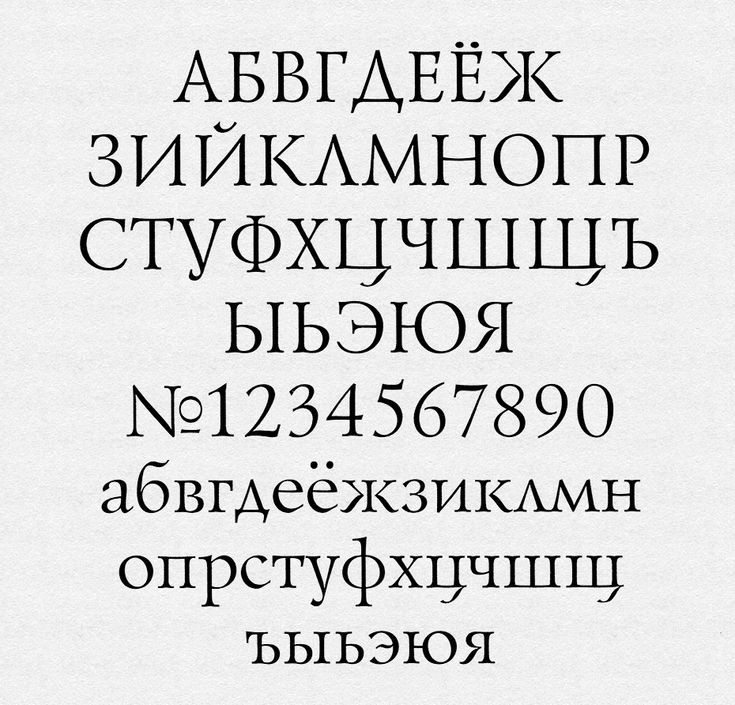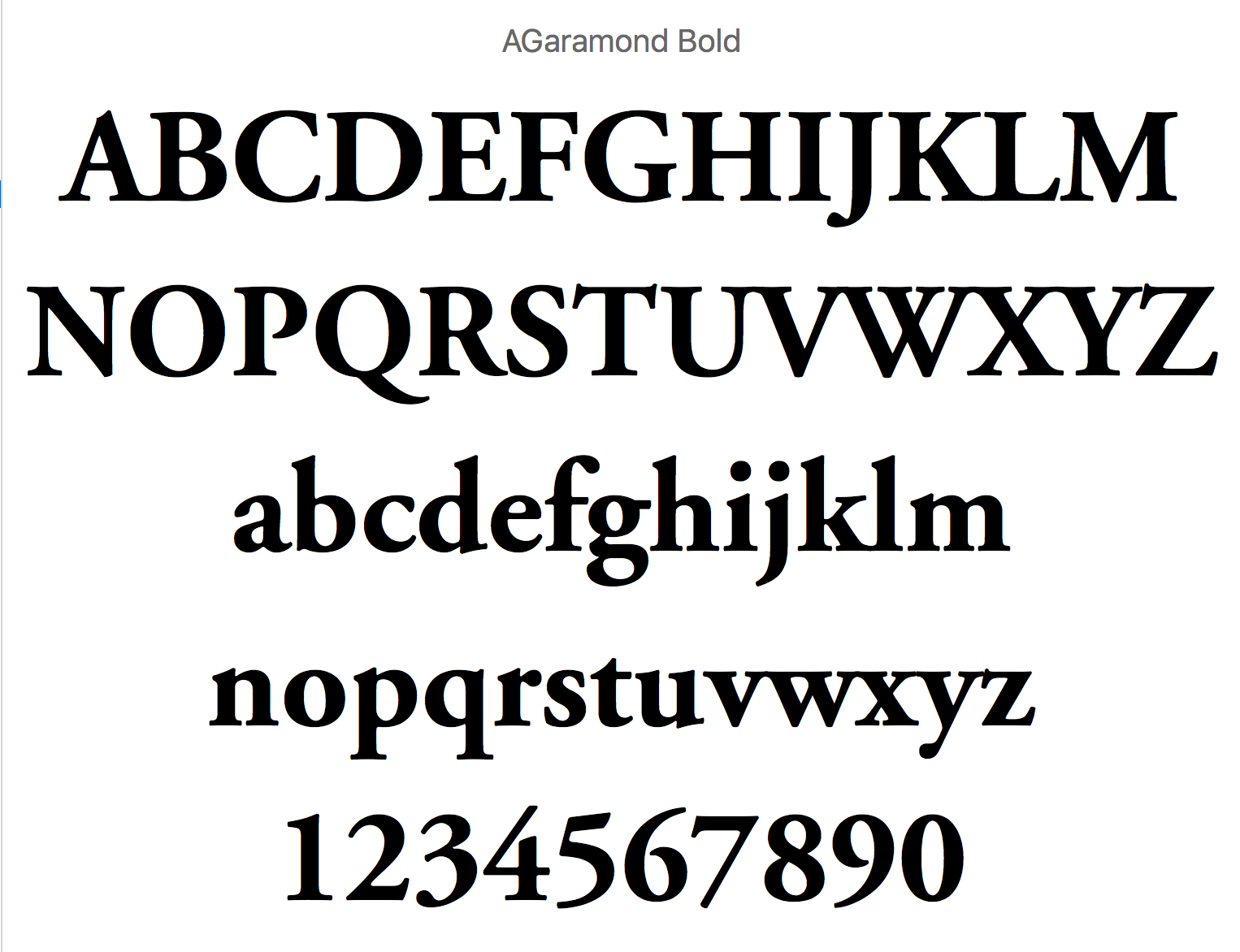
Наиболее часто используемые гарнитуры с засечками
Работа со шрифтами подразумевает понимание того, какие шрифты используются чаще всего в каждом из типов. Вы знаете, какие шрифты с засечками используются чаще всего? Волны Без засечек? Это то, что вы должны знать, чтобы знать тенденцию дизайна в то время или порвать с обычным и предложить клиенту что-то сверх обычного.
Итак, сегодня мы хотим сосредоточиться на наиболее часто используемые шрифты с засечками, Вы хотите знать, что это такое и почему? Мы вам тогда расскажем.
Что такое шрифт с засечками
Этот шрифт, также известный как serif, terminal или serifs, имеет орнаменты на концах персонажей, То есть на каждой букве есть красивый орнамент, который помогает сделать их визуально красивее.
Шрифт Serif отличается прежде всего тем, что он может меняться в зависимости от наклона, ширины, большого веса … Вот почему он делает его одним из лучших вариантов в зависимости от того, какие проекты. Например, для книг, логотипов, плакатов и т. Д. В общем, любой длинный текст может выиграть от этого шрифта, потому что он облегчает чтение, а также создает своего рода воображаемую строку, чтобы не потеряться.
Что передает шрифт Serif?
Шрифт с засечками считается одним из самых классических. Потому что, Иногда это называют «римской типографикой», потому что она передает эту формальность, сохранение, традицию и т.
Конечно, сегодня существует два типа засечки, древнеримские, чьи засечки уточняются по мере того, как они достигают крайности; и современные римские, сохраняющие толщину всей буквы.
Однако все они дают ощущение серьезности, авторитета, культа … Следовательно, они широко используются, особенно в книгах и образовательных проектах, благодаря своей трезвости.
Наиболее часто используемые шрифты с засечками
Как мы уже говорили, шрифты с засечками являются частью нашей повседневной жизни. Газеты, журналы, книги, учебники и др. Они предлагают нам этот тип шрифта, и мы рассматриваем их как нечто естественное, хотя мы не знаем, что они так называются.
Но из всех типов этого типа, какие шрифты с засечками используются чаще всего? Если хотите знать, мы поговорим о них ниже.
Times New Roman, один из наиболее часто используемых шрифтов с засечками
Это один из самых известных, особенно потому, что Word использует его с самого начала, и мы знаем это по работе с документами.
Он довольно четкий и имеет правильный размер, чтобы читать без особой головной боли.
Garamond
Garamond — один из самых используемых и распространенных шрифтов с засечками в мире. Если ты не знаешь Он был создан в XNUMX веке во Франции. Его создатель? Дизайнер Клод Гарамонд, отсюда и его имя.
Apple — одна из компаний, которые использовали его в течение многих лет, и он идеально подходит для учебников, веб-сайтов и т. Д.
Палатино Линотип
Это классический и распространенный шрифт с засечками, особенно в газетах, но также и в книгах, журналах и даже на веб-страницах, потому что они делают текст очень разборчивым.
Это системный шрифт, то есть установлен по умолчанию практически на всех компьютерах.
Книжник Старый Стиль
Это было разработан Онг Чонг Ва в 2005 году и имеет возможность предлагать вам до 12 шрифтов. Однако автор использовал более ранний шрифт Oldstyle Antique, разработанный в 1858 году компанией AC Phemister по заказу литейного завода Miller and Ricard в Эдинбурге, Шотландия.
После успеха многие другие американские компании создали различные версии книги, в результате чего появился Bookman.
Еще один из наиболее часто используемых шрифтов с засечками — Georgia.
Шрифт Georgia похож на шрифт Garamond, но более тонкий и плоский, чем Times New Roman. Он также меньше, поэтому занимает меньше места, чем другие буквы как и предыдущий, Bookman Old Style.
Как и те, о которых мы говорили, он хорошо известен, и мы установили его на компьютер.
Форум
Основанный на самых классических шрифтах, это один из наиболее широко используемых шрифтов с засечками, особенно в заголовках и заголовках. Однако это не значит, что его можно использовать только для этого.
Его создатель Денис Машаров придумал для использования в абзацах или длинных текстах.так как он выглядит довольно большим, и за ним легко следить.
Афина
Это один из наиболее широко используемых шрифтов с засечками, разработанный Мэттом Эллисом.
Можно сказать, что это один из самых классических (древнеримских). Почему? Ну, потому что окончания букв имеют тенденцию «утончаться» на концах, что характерно для этого типа шрифтов.
Однако в данном случае это придает ему смелый и в то же время эффектный вид, потому что, поскольку вся буква не одинакова, она привлекает внимание. В длинном тексте у вас не будет проблем с этим.
Бодони
Это один из наиболее часто используемых шрифтов с засечками, хотя его создание довольно старое. И сделал его создатель в 1787 году. Джамбаттиста Бодони была ветераном и опередила свое время. потому что он сделал шрифт современного кроя, который использовался во многих редакционных статьях, модных журналах и т. д.
Конечно, текущая версия — не та, которую делали в свое время. Этот новый называется Bauer Bodoni.
Плантен
Хотя это не очень известный шрифт, правда в том, что он был одним из самых используемых в 2020 году в гарнитурах с засечками, а это означает, что в этом году вы также можете рассмотреть его.
Используется в основном для редакционной работы, а также для непрерывных текстов. потому что его чтение очень приятно глазу и заставляет погрузиться прямо в текст, забыв обо всем остальном.
Часовой
Это один из наиболее часто используемых шрифтов с засечками с момента его создания в 2009 году. Его форма заставляет нас думать о курсиве, хотя буква не имеет прямого отношения к нему. Его легко понять, и в нем есть несколько строк, которые побуждают вас смотреть только на этот тип шрифта..
Есть еще много шрифтов с засечками, некоторые из характеристик этого шрифта даже выходят за рамки «нормального». Такие названия, как Book Antiqua, Libre Baskerville или Alegreya, — это лишь некоторые из других примеров наиболее часто используемых шрифтов с засечками, которые мы можем дать вам. Вы порекомендуете некоторые из них?
Шрифт с засечками
Объединенный институт ядерных исследований
- Информация о материале
- Категория: XX век.
Повседневная жизнь научного сотрудника
Не можем не поделиться с вами вот такой красотой: поздравительные адреса ручной работы. Это сейчас всё просто: скачал в яндексе фон для открытки и подходящее случаю стихотворение, выбрал шрифт, заполнил поздравление и распечатал на принтере.
А вот в XX веке… Главный секрет успеха — сотрудник с талантом каллиграфически писать. И другой, который умеет складно придумывать тексты. Невероятное терпение. Тушь и перо. Бритвенное лезвие для зачистки ошибок.
А если еще кто-то может акварелью выписать затейливую буквицу и нарисовать обложку…
На фото: поздравительные адреса к юбилеям Бруно Понтекорво от сотрудников ОИЯИ и других организаций.
Читайте также
Приглашаем на выставку «Рабочие будни научного сотрудника XX века»
08 апреля 2021
С 12 апреля по 12 августа приглашаем посетить выставку «Рабочие будни научного сотрудника XX века», приуроченную к 65-летию ОИЯИ!
В Музее истории науки и техники ОИЯИ представлены экспонаты из.
Пятничная рубрика: прощаемся и до скорой встречи в Музее ОИЯИ!
19 марта 2021
Дорогие друзья! Сегодня заключительный пост нашей пятничной рубрики «Повседневная жизнь научного сотрудника XX века», посвященной 65-летию нашего Института.
Стенгазета «Луч»
12 марта 2021
В прошлом выпуске мы писали о стенгазетах лабораторий ОИЯИ.
Праздничная стенгазета
05 марта 2021
Скоро праздник. Как тут не вспомнить о народном творчестве, которое кипело в кабинетах лаборатории в преддверии праздников и юбилеев, когда сотрудники создавали настоящие поздравительные шедевры для…
Говорят все радиостанции Советского Союза
26 февраля 2021
Сегодня человек с наушниками нам совершенно привычен.
Печатное слово
19 февраля 2021
Профессия машинистки, «женщины, работающей на пишущей машинке» (словарь Ушакова), уже ушла в прошлое. И хотя машинистка печатает быстро (и в этом смысле могла бы быть востребована и сегодня), ее уже…
Бумажная версия
12 февраля 2021
Споры между читателями электронных книг и приверженцами старой доброй бумаги давно утихли.
Войны остро- и тупоконечников не случилось. Кто-то полностью перешел на цифровые книги, кто-то остался…
Гарнитура из прошлого
05 февраля 2021
Вот такая трогательная гарнитура из прошлого века имеется в экспозиции Мемориального кабинета Бруно Понтекорво в ЛЯП ОИЯИ. Полагаем, что это устройство для делегатов международных конференций, с…
Шрифт с засечками
29 января 2021
Не можем не поделиться с вами вот такой красотой: поздравительные адреса ручной работы.
Это сейчас всё просто: скачал в яндексе фон для открытки и подходящее случаю стихотворение, выбрал шрифт,…
Миром правят числа
И снова мы делаем нашу рубрику совместно с Музеем истории науки и техники ОИЯИ. Потому что хотим рассказать о том, как считали в науке XX века. Точнее, производили большие и сложные расчеты,…
«Компактный, красивый, таинственно поблёскивающий…»
15 января 2021
Этот пост мы подготовили совместно с Музеем истории науки и техники ОИЯИ.
⠀
Цитата в заголовке о компьютере! Думаете, о новом смартфоне известной фирмы? Нет, это о вымышленном компьютере «Алдан-3″…
«Новый год, он не ждет, он у самого порога!»
25 декабря 2020
Дорогие друзья! В следующую пятницу мы с вами окажемся в новом, 2021 году, а значит, сегодняшний выпуск рубрики последний в нынешнем!
«Бабу-Ягу со стороны брать не будем — воспитаем в своём коллективе!»
18 декабря 2020
Если ваши родители или бабушки-дедушки работали в Институте в прошлом веке, то, наверняка, вам приходилось слышать, какая интересная и творческая жизнь кипела тогда в ученом сообществе в свободное.
Ручная работа
11 декабря 2020
В научных работах, помимо формул и текста, часто можно встретить и «рисунки». Надо заметить, что современная компьютерная графика началась во многом с графики научной и инженерной, ведь первые…
Прозрачный фон
04 декабря 2020
Подготовка к конференции или семинару — дело непростое.
Систематизировать информацию, написать и отредактировать текст, подготовить иллюстрации и графики и, наконец, собрать из этого презентацию.
«Пиво отпускается только членам профсоюза!»
27 ноября 2020
Эта цитата из «Двенадцати стульев» давно стала мемом. Она отражала реалии конца 20-х: членам профсоюзов полагались не только пиво, но и другие блага. Распределение благ вообще было вотчиной…
«… чтобы не нарушать отчетности!»
20 ноября 2020
Завтра, 21 ноября, День бухгалтера — специалиста, без которого не получится ничего.
И делать большую науку не получится тоже.
Предъявите ваш билет
13 ноября 2020
У каждого ученого XX века была стопка книжечек, подтверждающих его принадлежность к различным общественным организациям. Например, к Всесоюзному обществу «Знание». Помните докладчика из комедии…
Ноябрьские праздники
06 ноября 2020
Да, в этом году они уже прошли.
Но в XX веке «ноябрьские» отмечали 7 ноября, в день, когда произошла Октябрьская революция, с прилегающими выходными.Конечно, это были праздники! Во-первых, лишний…
Альбомы на антресолях
30 октября 2020
Есть отличный старый анекдот про интеллигента, который изящно выпроваживает засидевшихся гостей предложением достать еще семнадцать семейных фотоальбомов с антресолей.
- Вы здесь:
- Главная
- org/ListItem»> Новости лаборатории
Бесплатные крутые шрифты для уникального и креативного дизайнаDesigne-R
Создаете ли вы эскиз на YouTube, пост в Instagram или крутой постер, отличный шрифт – ключ к успешному дизайну. Вместо использования системных шрифтов по умолчанию вам нужны уникальные, привлекающие внимание шрифты, которые придадут вашему дизайну уникальную индивидуальность.
В этой статье мы представляем вам невероятную коллекцию бесплатных классных шрифтов для загрузки и создания красивого текста. С помощью этих шрифтов вы можете добавить чувство стиля к любому типу дизайна и сделать его действительно выделяющимся.
Эта коллекция включает в себя множество шрифтов, включая, элегантные шрифты с засечками, без засечек, декоративные шрифты, ретро-шрифты и многое другое, чтобы соответствовать любым и всем видам ваших дизайнерских работ. Все эти удивительные и супер классные шрифты можно бесплатно скачать.
Рекомендуем также посмотреть:
- Свежая и новая подборка шрифтов для ваших работ
- Топ лучших бесплатных шрифтов для дизайнеров
- Подборка Детских шрифтов в коллекцию дизайнеру
1. Шрифт Batuphat Script
Прекрасный жирный шрифт Batuphat Script доступен в двух стилях – Regular и Extrude и идеально подходит для создания многослойной типографики. Бесплатный для личного и коммерческого использования этот крутой шрифт от Debut Studio – отличный выбор для постеров, художественных принтов, дизайнов одежды и футболок, постов в Instagram и многого другого. Доступно для бесплатного скачивания в формате OTF.
2. Бесплатный шрифт The Night Watch
The Night Watch от дизайн-агентства Obys – это красивый бесплатный шрифт с засечками и уникальным дизайном. Вдохновленный и названный в честь картины Рембрандта ван Рейна «Ночной дозор» (1642 г.), этот шрифт поможет вам создать роскошную и мощную типографскую композицию.
Шрифт верхнего регистра, этот шрифт идеально подходит для заголовков, короткого текста, брендинга и логотипов. Бесплатная загрузка включает файл шрифта TTF.
3. Шрифт Lansdowne Decorative
Lansdowne черпает вдохновение из старой типографики рекламы. Это универсальный декоративный шрифт, сочетающий винтаж и классику с чистотой. Этот бесплатный шрифт, разработанный Twicolabs Fontdation, представлен в двух стилях – Regular и Slanted, а также в форматах TTF и OTF.
4. Lettown Hills Cool Display
Lettown Hills – это забавный бесплатный шрифт с набором закрученных букв. Классные алфавитные шрифты, подобные этому, отлично подходят для брендинга, рекламы или креативных заголовков. Шрифт, разработанный Senzana, предоставляется для бесплатного скачивания в формате OTF.
5. Alégra Minimal Sans Serif
Alégra – это бесплатный современный минималистичный шрифт без засечек с плавными изгибами.
Этот уникальный шрифт, созданный Black Font Labs, имеет стильный, но формальный футуристический вид. При загрузке вы получаете файлы шрифтов TTF и OTF.
6. Misto Font – (Cyrillic and Latin)
Шрифт Misto – это бесплатный шрифт, разработанный Катериной Королевцевой. Его уникальные структурированные буквы делают его привлекательным для заголовков, фирменных знаков, веб-сайтов, упаковки и плакатов. Загрузка включает шрифт в форматах TTF, OTF, Web Font. Misto поддерживает как кириллицу, так и латиницу.
7. Шрифт Little Bird бесплатный винтажный шрифт
Little Birds отличается современным винтажным дизайном букв с красивыми лигатурами, которые выделят ваш дизайн. Этот старинный скриптовый шрифт, выпущенный для бесплатной загрузки компанией Senzana, доступен в форматах OTF, TTF, EOT и WOFF.
8. Rokurou Display Font
Rokurou Display от Damelev Studio – элегантный шрифт с засечками и контрастными буквами, которые создают впечатление элегантности и роскоши.
Этот шрифт подойдет для любого творческого проекта. Доступно для бесплатного скачивания в форматах OTF и TTF.
9. Fungis Grotesque
Fungis от Milena Leimig – это бесплатное современное семейство шрифтов Sans Serif в трех стилях: Regular, Bold и Heavy. Его изгибы и вырезанные чаши в некоторых формах букв придают ему неповторимый вид. Шрифт бесплатный для коммерческого и личного использования, он поставляется в форматах TTF, OTF, WOFF и WOFF2.
10. Jangkuy Display
Jangkuy – отличный шрифт, который можно использовать для создания классных заголовков для плакатов, графики в социальных сетях, миниатюр видео и баннеров. Он имеет жирные широкие буквы. Шрифт можно использовать в личных и коммерческих проектах. Созданный Atas Project, Jangkuy представлен в 3 стилях – Обычный, Полужирный и Черный и доступен для бесплатного скачивания в формате OTF.
11.
PikoloPikolo Block Alt – это экранный шрифт с символами, состоящими из слегка закругленных линий, придающих ему уникальное игривое ощущение. Он черпает вдохновение из старинной гравюры на дереве. Этот крутой шрифт от студии графического дизайна Ideabuk идеально подходит для заголовков, заголовков и логотипов. Его можно бесплатно скачать в формате OTF.
12. Шрифт бесплатных заголовков Wild World
Wild World – еще один отличный бесплатный заголовок и шрифт заголовка. Созданный Абдуллой Мосадом, он имеет широкие жирные буквы и может быть загружен бесплатно в виде файла шрифта OTF.
13. Бесплатный шрифт Bourbon Grotesque
Bourbon Grotesque – это креативный дисплейный шрифт с ярким дизайном для создания привлекающих внимание заголовков, логотипов и плакатов. Бесплатное использование и доступное в формате OTF, разработанное Джереми Весси.
14.
Шрифт Cunia Bold Sans SerifCunia – это жирный шрифт без засечек со слегка закругленными углами, который придает тексту мягкость. Заглавный шрифт Cunia предназначен для заголовков и заголовков. Любезно предоставленный Алехо Бергманном, шрифт доступен для бесплатной загрузки в формате OTF.
15. Коллекция шрифтов Lil Stuart
Создавайте художественные проекты с помощью этой бесплатной пары, состоящей из рукописного шрифта и строгого шрифта без засечек. Идеально подходит для добавления типографского контраста и разнообразия в ваши проекты. Разработано Alphabeta и доступно для бесплатной загрузки в форматах OTF и TTF.
16. Бесплатный текстурированный шрифт Holtzberg
Holtzberg от Джереми Весси – еще один бесплатный винтажный шрифт, который отлично подходит для винтажных логотипов, ресторанов, парикмахерских, баров, кафе и т. Д. Шрифт имеет текстуру высокой печати, которая добавляет ему смелой эстетики.
Этот напористый шрифт станет заметным элементом любого дизайн-проекта, в котором он используется. Доступен для бесплатной загрузки в формате OTF.
17. Odachi Brush
Odachi – элегантный бесплатный шрифт с грубым размытым набором символов. Созданный Мехметом Рехой Тунджу, он совершенно бесплатен для использования в ваших коммерческих проектах. Загрузка включает файлы OTF и webfont.
18. Tablón Geometric Typeface
Создавая Таблон, дизайнер Кристиан Турнье черпал вдохновение в вывесках старых клубов в своем районе. Это семейство шрифтов трех степеней тяжести – Regular, Medium и Black, а также закругленного стиля для Black. Этот бесплатный геометрический шрифт добавит индивидуальности любому тексту, например заголовкам, обзорам журналов, книгам, плакатам, рекламе и брендингу. Доступно для бесплатного скачивания в формате TTF.
19. Bogam Bold Typeface
Bogam – бесплатный шрифт от Bagerich Type Foundry, вдохновленный городским стилем жизни, музыкой и модой.
Если вам нужно создать выделяющийся текст для логотипа или заголовка, все, что вам нужно, – это полужирный шрифт, такой как Bogam. Бесплатная загрузка включает файлы шрифтов TTF и OTF.
20. Шрифт подписи RedSky
RedSky – это потрясающий скриптовый шрифт для подписи, который добавит элегантности приглашениям, заголовкам, логотипам, сообщениям в социальных сетях и поздравительным открыткам. Вы можете сочетать его со шрифтом с засечками или без засечек, чтобы создать интересный дизайн. Этот роскошный скриптовый шрифт, созданный Masanis Studio, можно бесплатно загрузить в форматах OTF, TTF и Web Font.
21. Quantum Futuristic
Quantum – бесплатный жирный шрифт, вдохновленный играми, с футуристической атмосферой. Это отличный выбор для любого дизайна, связанного с играми, космосом и научной фантастикой, например для эскизов игровых видео на YouTube, футуристической графики в социальных сетях и брендинга.
Классные шрифты, такие как Quantum, помогут вам создать впечатляющую типографику. Разработанный Грегом «Сесохом» Ортисом, Quantum можно бесплатно загрузить в формате OTF.
22. Бесплатный шрифт Luam
Luam – это красивый и простой шрифт без засечек в трех стилях: Light, Regular и Bold. Он поставляется с полным набором знаков, цифр и символов. Этот бесплатный для коммерческого использования шрифт от Патрисии Кастро Васкес идеально подходит для брендинга и оформления заголовков. Формат шрифта: TTF и OTF.
23. Шрифт Moalang Display
Moalang – это стильный дисплейный шрифт с художественными изгибами и декоративными элементами. Шрифт отлично будет смотреться на обложках книг, постерах, флаерах, логотипах и многом другом. Шрифт, разработанный Swistblnk Studio, доступен для бесплатной загрузки в формате TTF.
24. Messenger Font
Бесплатный шрифт Messenger от Alex Joganic подходит для всех ваших винтажных тематических проектов, особенно для брендинга, графики на футболках и дизайна упаковки.
Шрифт представлен в 3 стилях – Обычный, Шероховатый и Текстурированный, которые идеально подходят для придания винтажного оттенка вашему дизайну. Формат шрифта: OTF.
25. Senilità Retro Display Font
Стильный геометрический дизайн Senilità вдохновлен ретро-стилями середины века и типографикой ар-деко. С помощью этого шрифта вы можете создавать эффектные заголовки и заголовки. Шрифт, разработанный Пьетро Филиппеши, можно бесплатно загрузить в формате OTF.
26. Бесплатный шрифт Silverfake Slab Serif
A contemporary slab serif font, Silverlake by Alexey Frolov features wide letterforms that will make your headlines stand out. The font is capital only but includes some alternate characters. Available for free download in TTF and OTF formats.
Узнать больше интересного:
25 лучших шрифтов с засечками, которые подойдут для вашего сайта
Говоря о брендинге, стиле и изысканном дизайне, мы обычно имеем в виду графику, анимацию и интуитивность интерфейса.
Но как насчет типографики? Это также оказывает сильное влияние на то, как посетители воспринимают ваш сайт.
Типографика сайта отражает имидж вашего бренда и должна гармонировать со всем интерфейсом. Эта роль может показаться не столь заметной на фоне других элементов веб-дизайна. Но если шрифт выбран неправильно, вы сразу увидите разницу. Поэтому, чтобы убедиться, что выбранный шрифт передает правильное сообщение, ищите идеальное соответствие.
Этот пост будет посвящен семейству шрифтов Serif, чтобы представить лучшие варианты среди сотен существующих. Погрузитесь, чтобы ознакомиться с этими лучшими образцами шрифтов с засечками, которые могут сделать ваш веб-сайт сбалансированным, надежным и удобным для пользователя.
Шрифты с засечками и без засечек. Какая разница?
Главной отличительной чертой шрифтов с засечками является наличие декоративных линий или конусов. Они размещаются на основах букв и на самом деле называются засечками.
Самыми популярными шрифтами с засечками являются Baskerville, Times New Roman и Georgia. Напротив, шрифты без засечек имеют буквы с чистыми линиями. Известными примерами шрифтов без засечек являются Arial, Helvetica и Calibri.
Но главное различие между шрифтами с засечками и без засечек заключается в сообщении, которое они передают для поддержки индивидуальности вашего бренда. Существует распространенный стереотип, что некоторые известные шрифты с засечками устарели, а шрифты без засечек представляют собой более современный контент. Однако оба семейства шрифтов активно используются в Интернете.
Дизайн шрифта с засечками олицетворяет надежность, серьезный подход и формальный стиль вашего сайта. Они уважительны и напоминают классические тексты книг и печатных изданий. Таким образом, шрифты с засечками станут отличным выбором для более традиционных бизнес-брендов. Они соответствуют стилю финансового сектора и крупных предприятий. Некоторым менее формальным компаниям также может быть полезно использовать шрифты с засечками в дизайне своих веб-сайтов.
Например, засечки становятся новой тенденцией на платформах электронной коммерции.
Дизайн шрифта без засечек передает простоту и минимализм. Он лучше применим для более молодой аудитории и связан с инновационными подходами. Вот почему шрифты без засечек часто используются ИТ-компаниями, стартапами и студиями креативного дизайна.
Шрифты с засечками: когда и где их лучше всего использовать?
Семейство шрифтов Serif занимает особое место в веб-типографике. Они лучше всего подходят, если ваш бренд должен производить солидное и официальное впечатление. Шрифты с засечками читабельны, просты и не отвлекают. Неудивительно, что они используются по умолчанию во многих текстовых редакторах, включая Microsoft Office и Apple Text Edit. Кроме того, шрифты с засечками традиционно выбирают всемирно известные газеты и журналы, такие как The New York Times, Boston Globe и т. д.
Шрифт с засечками на вашем веб-сайте вызывает чувство безопасности, уважения и значимости.
Современные шрифты с засечками также отлично подходят для логотипов, визитных карточек и брошюр. Прежде чем использовать один из этих шрифтов для своего веб-сайта, убедитесь, что он соответствует стилю и ценностям вашей компании. Крайне важно достичь цели и оправдать ожидания вашей аудитории.
Лучшие примеры шрифтов с засечками
Для вашего удобства мы собрали список шрифтов с засечками, в котором представлены лучшие образцы этого семейства шрифтов. Каждый из них в чем-то особенный и может стать отличным выбором для веб-сайта вашей компании, в зависимости от стиля вашего бренда и вашего личного вкуса.
Didot
Этот неоклассический шрифт напоминает стиль эпохи Возрождения. Didot идеально подходит для заголовков и логотипов, чтобы выглядеть элегантно и формально. Например, он используется для обложки журнала Vogue с 1955 года. Он также используется для нового логотипа Zara.
Шрифт Didot, используемый для оформления журналаTimes New Roman
Этот классический шрифт, созданный в 1931 году для газеты The Times, до сих пор популярен и имеет различные версии.
Times New Roman используется в качестве системного шрифта Microsoft Office. На сайтах это выглядит надежно и уважительно.
Georgia
Еще один известный пример шрифта Serif, Georgia, отлично читается. Вот почему он часто используется как для основного текста веб-сайтов, так и для приложений электронных книг.
Пример дизайна шрифта GeorgiaCourier New
Этот шрифт напоминает традиционную типографику, поскольку он был создан для пишущих машинок IBM. Позже Courier New был представлен как компьютерный шрифт. Вы можете использовать такие специальные моноширинные шрифты для имитации старомодного набора текста или исходных кодов программирования.
Плакат с шрифтом CourierAdobe Garamond Pro
Благодаря своей удобочитаемости шрифты Garamond часто используются для печатных книг и основного текста. Garamond Pro был разработан для Adobe Systems и до сих пор считается одним из самых удобных шрифтов для чтения.
Argesta
Argesta — модный и элегантный шрифт с засечками, который идеально подходит для логотипа бренда, изысканного веб-сайта или дизайна журнала. Argesta прекрасно сочетает винтажный и современный стили.
Argesta, вневременной и элегантный шрифт с засечкамиAmerican Typewriter
Благодаря знаменитому логотипу «I Love New York» вы, вероятно, знакомы с этим шрифтом. American Typewriter — еще один отличный вариант для тех, кто ищет стильный шрифт с засечками.
Пример дизайна журнала для американских пишущих машинокBookman Old Style
Bookman Old Style немного жирнее обычных шрифтов с засечками, поэтому его часто используют в заголовках и логотипах, которые должны привлекать внимание. Bookman может быть стильной отсылкой к традиционному графическому дизайну 19-го века.60-е годы.
Пример шрифта Bookman Old StyleGoudy Stout
Фредерик Гауди создал этот эффективный шрифт с засечками в старом стиле в начале 20 века.
Среди солидных шрифтов с засечками Goudy Stout довольно легкомысленный, но все же выглядит винтажно и стильно.
Cambria
Cambria — один из самых популярных вариантов для веб-дизайна, особенно хорошо адаптированный для основного текста. Он был специально создан для чтения с экрана, имея ровные пространства и пропорции. Cambria широко используется Microsoft и остается шрифтом по умолчанию для многих приложений.
Плакат со шрифтом CambriaОдежда
Этот декоративный шрифт с тонкими штрихами станет отличным выбором для тех, кто хочет, чтобы их сайт выглядел свежо и современно. Вы можете использовать одежду для заголовков, логотипов или фирменного стиля.
Пример шрифта для одеждыBeirut
Beirut — выдающийся шрифт, идеальный вариант для того, чтобы придерживаться последних тенденций в каллиграфии. Этот шрифт имеет две доступные версии и выглядит особенно элегантно в темном режиме. Шрифт
Beirut используется для дизайна веб-сайтаJuana
Juana выглядит гармонично и стильно, благодаря сочетанию толстых и тонких мазков.
Это может выглядеть слишком декоративно для основного текста, но будет идеальным выбором для логотипов, заголовков и брендинга.
Lora
Этот шрифт — еще один отличный выбор для основного текста вашего веб-сайта. Он хорошо читается, но немного более современен, чем Baskerville и Times New Roman. Этот шрифт будет отличным вариантом для длинных чтений, таких как сообщения в блогах.
Пример шрифта ЛораGiveny
Giveny предлагает округлые формы букв, которые выглядят художественно, геометрично и гармонично. Это может выглядеть необычайно своеобразно, если вы используете его для названия дизайна, художественной цитаты или брендинга. Giveny кажется одинаково подходящим для бизнеса и искусства.
GivenyMaiah
Если вы предпочитаете элегантность и минимализм для своего веб-сайта, Maiah может стать лучшим выбором. Он одновременно строгий и деликатный, что делает его подходящим для заголовков, презентаций, заголовков, веб-макетов, рекламы и т.
Butler
В этом шрифте удачно сочетаются традиционно строгие штрихи с засечками и современные привлекательные изгибы. Таким образом, шрифт Butler поможет привлечь внимание и выделить то, что должно быть заметно.
ButlerQuincy
Quincy может пригодиться, если вы ищете более дружелюбные шрифты с засечками без типичной классической атмосферы. Этот шрифт довольно игривый и расслабляющий, его закругленные элементы кажутся оптимистичными и ненавязчивыми.
QuincyRostemary
Rostemary — новый шрифт с засечками для творческого дизайна. Он может привнести элегантность в любой проект, будь то название фильма, логотип или страница блога.
Rostemary, пример элегантного шрифта с засечкамиBogart
Этот шрифт с засечками, названный в честь голливудской кинозвезды Хамфри Богарта, прекрасно передает ностальгию по нуару и старомодной поп-культуре. Это особенно хорошо для гладких и броских заголовков или цитат.
Noir et Blanc
Noir et Blanc Гарнитура выглядит загадочно и самобытно. У него есть отличный шанс произвести впечатление на вашу аудиторию, поскольку он относительно новый и не используется слишком часто. Noir et Blanc может сделать дизайн чувственным и свежим.
Noir et Blanc Пример шрифта с засечкамиRespace
Этот стильный неоклассический шрифт с засечками представляет собой сбалансированное сочетание винтажного и современного стилей. Его контраст и геометрия идеально подходят для того, чтобы подчеркнуть современный вид вашей страницы. Respace можно использовать для брендинга, заголовков, оформления журналов, плакатов и т. д.
Пример стильного шрифта с засечками RespaceRoslindale
Шрифт Roslindale отсылает к известному американскому принтеру De Vinne, смело модернизируя его старый стиль. Вы можете использовать его для поддержки выдающегося графического дизайна вашего веб-сайта, плакатов и искусства.
RoslindalePlayfair Display
Этот шрифт является прекрасным представителем переходного дизайна.
Предпочитаете Баскервиль и обожаете Грузию за тексты? Вы можете найти Playfair Display достойной альтернативой более типичным вариантам.
Harmond Serif
Этот шрифт идеально подходит для отображения больших размеров текста. Harmond Serif — это декоративный шрифт, который привнесет в ваш дизайн нотку модности и стильной каллиграфии.
Хармонд с засечкамиВыберите правильный вариант для своего веб-сайта
Шрифты с засечками отличаются от других шрифтов тем, что они делают текст классическим и изысканным, но при этом простым и читабельным. Они могут идеально подойти для веб-сайта, который должен производить впечатление серьезности и надежности. Кроме того, шрифты с засечками хорошо подходят для заголовков, логотипов, визитных карточек и т. д.
Надеемся, наши тщательно отобранные примеры шрифтов с засечками помогли вам найти правильный вариант для вашего веб-сайта. Но если вам нужна более подробная консультация по выбору шрифтов или любых других дизайнерских решений, смело обращайтесь к нашей команде.
Мы в Fireart Studio готовы предложить любые идеи по созданию или редизайну вашего сайта, сделав все его элементы сбалансированными, современными и выдающимися.
Обновление:
100+ лучших современных шрифтов с засечками 2022
Пришло время погрузиться в коллекцию лучших красивых современных шрифтов с засечками. Шрифты с засечками идеально подходят для печатной литературы, детальной типографики или для создания более формального эффекта. И эти популярные шрифты с засечками действительно выделяются из толпы.
Мы собрали более 100 лучших современных шрифтов с засечками, которые вы можете быстро начать использовать в своей работе. Вы будете поражены тем, какую разницу они могут внести в ваш дизайн-проект по сравнению с более общими системными шрифтами, которые слишком часто используются.
Нет ничего лучше четкого шрифта с засечками , чтобы действительно выделить ваш макет и создать что-то красивое.
Многие шрифты с засечками рискуют показаться немного устаревшими. Не эти. Наш выбор современных шрифтов с засечками выглядит свежим, инновационным и готовым к созданию дизайнерских работ, задающих тренд! А наши советы по выбору современного шрифта с засечками помогут вам выбрать именно тот, который подходит для вашего проекта.
2 миллиона шрифтов, гарнитур и дизайнерских ресурсов с неограниченным количеством загрузок
Загрузите тысячи премиальных шрифтов и гарнитур с членством в Envato Elements. Он начинается с 16 долларов в месяц и дает вам неограниченный доступ к растущей библиотеке из более чем 2 000 000 шрифтов, шаблонов дизайна, тем, фотографий и многого другого.
Шрифты без засечек
Новый и свежий
Шрифты с засечками
Современный и стильный
Декоративные шрифты
Винтаж и уникальный
Шрифт Abang Typeface
Шрифт без засечек
Буквенное ремесло
Сценарий
Скриптовые шрифты
Кисть + сценарий
Исследуйте шрифты
Лучший выбор
Pomino — это семейство шрифтов с засечками, которое поставляется с несколькими стилями, из которых вы можете выбирать для создания различных профессиональных дизайнов.
Семейство шрифтов включает 3 разных стиля с легким, обычным и полужирным шрифтом. В качестве дополнительного бонуса он также поставляется с 15 абстрактными формами в векторных форматах файлов.
Почему это лучший выбор
Элегантный дизайн этого семейства шрифтов с засечками выделяет его из толпы. Узкий интервал и несколько весов позволят вам использовать этот пакет шрифтов для создания многих типов креативных печатных и цифровых дизайнов.
Если вам нужен дизайн с нотками ретро и ностальгии, но в то же время современный, обратите внимание на Northden. Это шрифт с засечками и промышленным дизайном, который гарантированно выделит вашу работу и сделает вас профессиональным дизайнером среди коллег и клиентов.
Если вы ищете многоцелевой шрифт с засечками, который вы можете использовать для дизайна всего, от креативных логотипов до элегантных визитных карточек, этот шрифт идеально вам подходит. Anko — это современный шрифт с засечками, отличающийся элегантным и стильным дизайном.
Он включает в себя 8 различных весов с 450 глифами.
Используйте этот толстый и жирный шрифт с засечками для создания креативных названий и заголовков для ваших проектов. Он особенно подходит для создания заголовков веб-сайтов, заголовков постеров и даже современных логотипов. Шрифт имеет разную насыщенность от тонкой линии до черного и включает 400 глифов.
Lavish — элегантный шрифт с засечками со стильными четкими буквами. Он идеально подходит для создания дизайна упаковки для брендов класса люкс и продуктов высокого класса. А также логотипы и значки для современного бизнеса, посты в социальных сетях, заголовки веб-сайтов и многое другое.
Willton — это элегантный шрифт с засечками, в дизайне которого используются элементы как старинных, так и современных эпох. Он идеально подходит для разработки логотипов, этикеток продуктов, обложек книг, названий плакатов и многого другого.
Это трафаретная версия популярного шрифта с засечками Quas. Он отличается той же элегантностью, что и его оригинальный дизайн, но с креативным трафаретным дизайном.
Этот шрифт идеально подходит для создания логотипов, заголовков и постеров для брендов класса люкс.
Kenjo — это коллекция современных шрифтов с засечками, дизайн которых вдохновлен японским искусством и украшениями. Он наиболее подходит для создания логотипов и других дизайнов для брендов моды и одежды.
Madelin — это современный шрифт с засечками, отличающийся толстым геометрическим дизайном, который выделяет его из толпы. Шрифт поставляется в 5 различных стилях шрифта, включая закругленные и контурные шрифты.
Этот креативный шрифт с засечками идеально подходит для создания логотипов модных брендов, предметов одежды и предметов роскоши, а также дизайна канцелярских принадлежностей. Шрифт поставляется в 2 стилях и версии веб-шрифта.
Для создания эффекта беззаботного наброска от руки обратите внимание на Мадлен. Это симпатичный шрифт с засечками, тщательно разработанный, чтобы придать вашим проектам уникальный вид. Таким образом, мы рекомендуем вам попробовать Мэдлин или, по крайней мере, добавить ее в свой список.
Созданный по образцу типографики в стиле 90-х годов, которую обычно можно увидеть на флаерах, плакатах и обложках книг, Ocean Twelve — это современный шрифт с засечками, который придаст вашим проектам красивый штрих ручной работы. Это отличный выбор для широкого спектра творческих и профессиональных приложений!
Lansdowne — идеальный кандидат, чтобы утолить жажду винтажного классического шрифта. Наклонный шрифт Lansdowne, состоящий только из заглавных букв, обладает мощным ударом и поставляется в комплекте со стандартными прописными и строчными буквами, цифрами, пунктуацией и многоязычной поддержкой.
Идеальный выбор для поздравительных открыток, дизайнов футболок, плакатов и других материалов для брендинга. Glowist — потрясающий шрифт, который обязательно сделает смелое заявление. Он поставляется с альтернативными персонажами и орнаментами, облегчающими создание произведений искусства, достойных внимания. Один из лучших шрифтов с засечками
Если вы хотите получить отличный шрифт с засечками, не потратив ни копейки, Satisfice поможет вам.
Это чистый современный шрифт, который идеально подходит для различных проектов и содержит прописные и строчные буквы, цифры, знаки препинания и символы. Это один из лучших шрифтов с засечками в нашем списке!
Конечно, странное название для шрифта, но дизайн и стильный вид этого шрифта с засечками делают его незаменимым шрифтом для профессионалов. Четкий дизайн букв и креативные геометрические формы придают этому шрифту уникальный внешний вид. Он также включает в себя 11 различных начертаний шрифта.
Kenfolg — красивый шрифт с засечками, который вы можете бесплатно скачать и использовать в своих личных проектах. Бесплатная версия включает в себя ограниченные функции, но этого более чем достаточно, чтобы придать профессиональный вид вашим небольшим проектам.
С первого взгляда видно, как классно выглядит этот шрифт. Он отличается определенным элегантным видом, непохожим ни на один другой. Чистый дизайн букв, смешанный с современным стилем, делает его отличным шрифтом для разработки заголовков для брендинга, заголовков веб-сайтов и многого другого.
Если вы ищете минималистичный шрифт, чтобы придать своим проектам профессиональный вид, этот шрифт идеально вам подойдет. Это шрифт с засечками, который также имеет стиль толстых букв. Он идеально подходит как для печати, так и для цифрового дизайна.
Поиск правильного вторичного шрифта, соответствующего шрифту заголовка, часто может занимать много времени. Но с этим дуэтом шрифтов вам не нужно об этом беспокоиться. Этот пакет поставляется с парой современных шрифтов, включая шрифт с засечками и рукописный шрифт. Оба идут очень хорошо вместе. В качестве бонуса он включает в себя шаблон логотипа в векторном формате.
Этот современный шрифт с засечками отличается роскошным дизайном. Он идеально подходит для создания этикеток, логотипов и заголовков для ваших высококачественных продуктов и брендинга. Шрифт также включает в себя множество лигатур и альтернативных символов.
Этот бесплатный шрифт с засечками имеет очень необычный дизайн символов. У каждого персонажа есть шероховатые края, которые делают его довольно креативным.
Это позволит вам придать некоторую индивидуальность вашим проектам. Шрифт можно бесплатно загрузить и использовать в личных и коммерческих проектах.
Cholens — это шрифт с закругленными засечками, излучающий роскошь и элегантность. Этот бесплатный шрифт можно использовать для целого ряда проектов, от плакатов, логотипов, открыток и журналов до обложек YouTube, презентаций, этикеток и многого другого. Возьмите его прямо сейчас.
Carentro — еще один элегантный шрифт с засечками, созданный специально для роскошных и элитных брендовых дизайнов. Этот шрифт идеально подходит для создания всего: от логотипов до визитных карточек, канцелярских принадлежностей и многого другого. Он включает в себя набор символов, состоящий из заглавных букв, с альтернативами и лигатурами.
Как и название, этот дисплейный шрифт также демонстрирует определенный профессионализм в дизайне персонажей. Его стильный внешний вид идеально впишется как в деловой, так и в повседневный дизайн, включая футболки и даже поздравительные открытки.
Это ручной шрифт с засечками, выполненный в современном дизайне. Несмотря на то, что на предварительном изображении шрифт демонстрирует ретро-стиль, вы можете легко использовать этот шрифт в современном дизайне с правильной комбинацией цвета и фона.
Linford — отличный выбор для того, чтобы придать вашему дизайну особый шарм. Это смелый и элегантный шрифт, который будет хорошо смотреться на поздравительных открытках, заголовках, баннерах, плакатах, рекламных щитах, цитатах, а также на различных элементах брендинга и упаковки.
Kohm — это шрифт с засечками, отличающийся стильным винтажным дизайном. Этот шрифт идеально подходит для оформления плакатов, баннеров и заголовков веб-сайтов. Он включает заглавные буквы, цифры и многоязычные буквы.
Troye — это элегантный бесплатный шрифт, который вы можете использовать для создания роскошного брендинга и бизнес-дизайна высокого класса. Шрифт также идеально подходит для логотипов. Это бесплатно для использования с личными проектами.
Giveny — это современный шрифт с засечками и роскошным дизайном. Он отличается четким дизайном букв, который позволяет вам продемонстрировать элегантность и класс. Он идеально подходит для дизайна, связанного с брендами класса люкс и высокого класса.
Nandia — креативный шрифт с засечками, который идеально подходит для создания повседневных и повседневных дизайнов. Шрифт имеет стильный и привлекательный дизайн, который отлично сочетается с дизайном футболок, дизайном социальных сетей и даже логотипом.
Хотите вариант без наворотов? Обратите внимание на Wensley, простой и элегантный стиль шрифта, который обязательно привлечет к вашим проектам внимание, которого они достойны. Это золотой стандарт в мире современных шрифтов с засечками.
Высокий и узкий дизайн этого шрифта, безусловно, сделает ваши проекты уникальными. Этот шрифт с засечками имеет смешанный современный и винтажный дизайн. И это идеально подходит для высококачественного дизайна модного брендинга.
Это шрифт с заглавными буквами, многоязычными символами, лигатурами и цифрами.
Если вы работаете над дизайном логотипа или этикетки для современного бренда класса люкс, Tonic — это великолепный шрифт с засечками, который вы можете использовать для создания своего дизайна. Этот шрифт имеет очень чистый и минимальный дизайн букв. И это хорошо работает как для печатного, так и для цифрового дизайна.
Marmo — это семейство шрифтов с засечками, включающее 5 различных начертаний и курсив. Этот шрифт можно загрузить и использовать совершенно бесплатно даже в коммерческих проектах.
Благодаря необычному дизайну букв этот шрифт с засечками поможет придать необычную индивидуальность вашему современному и повседневному дизайну. Шрифт включает в себя как прописные, так и строчные буквы, а также лигатуры.
Следующим в нашем списке лучших современных шрифтов с засечками идет Siggy, искренний шрифт с засечками, который слегка покачивается. Это может быть отличным дополнением к вашим дизайнерским проектам, поэтому используйте его с уверенностью.
Еще один современный роскошный шрифт с засечками для создания логотипов, этикеток, листовок и визитных карточек для брендов и продуктов высокого класса. Этот шрифт имеет толстый дизайн букв, который будет отлично смотреться практически на любой поверхности.
Не каждый день увидишь написанный вручную шрифт с засечками. Этот шрифт определенно выделит ваш дизайн из толпы. Он имеет очень естественный вид, нарисованный от руки, который добавит индивидуальности вашим творениям.
Coldiac — это чистый роскошный шрифт с очень элегантным дизайном букв. Тонкий и просторный дизайн этого шрифта делает его отличным выбором для разработки логотипов и этикеток для современных и роскошных брендов.
Этот элегантный шрифт с засечками можно использовать совершенно бесплатно. Он имеет современный и стильный дизайн, что делает его отличным выбором для создания заголовков веб-сайтов, постов в социальных сетях, плакатов и многого другого.
Этот бесплатный шрифт имеет дизайн в винтажном стиле, который можно использовать для создания профессиональных логотипов, заголовков и визитных карточек.
Бесплатная версия шрифта доступна только для личных проектов.
Простой и элегантный дизайн этого шрифта с засечками делает его идеальным выбором для разработки сложных логотипов брендов в сфере моды и предметов роскоши. Он включает в себя все основные символы, символы и знаки препинания.
Maiah — это семейство шрифтов с засечками, которое поставляется с 4 различными весами шрифта, от светлого до полужирного. Он содержит как прописные, так и строчные буквы, а также многоязычные символы и знаки препинания.
Если вы ищете забавный и необычный шрифт с засечками, Mailtoon — идеальный шрифт для вас. Он отличается креативным дизайном, который позволит вам легко выделить заголовки и заголовки, особенно при создании дизайнов, удобных для детей.
Merova — это современный шрифт с засечками, дизайн которого вдохновлен классическими гарнитурами. Он создан специально для создания логотипов и вывесок для продуктов высокого класса и брендов класса люкс. Шрифт также имеет 5 различных начертаний.
Abell — это семейство уникальных шрифтов с 8 различными весами шрифтов, которые позволят вам создавать все виды дизайна для бизнеса и брендинга. Шрифт включает как прописные, так и строчные буквы, а также многоязычные символы.
Riffle — высокий узкий шрифт с засечками, который идеально подходит для создания заголовков для постеров и заголовков веб-сайтов. Шрифт включает в себя заглавные буквы и множество глифов. Это бесплатно для использования с личными проектами.
Этот красивый шрифт с засечками отличается элегантным дизайном в винтажном стиле. Он включает в себя набор символов с прописными и строчными буквами с привлекательными изгибами. Это бесплатно для использования с личными проектами.
Если вы работаете над креативным дизайном поздравительной открытки, плаката или даже обложки для социальных сетей, этот современный шрифт с засечками поможет придать вашему дизайну уникальный штрих. Вы также можете использовать его для создания логотипов, поскольку он также поставляется с набором из 24 готовых шаблонов логотипов.
Jerrick — это современное семейство шрифтов с засечками, которое включает в себя 6 различных начертаний, от обычного до полужирного и курсивного. Шрифт содержит как прописные, так и строчные буквы с многоязычными символами. Это универсальный шрифт, который вы можете использовать для оформления всего: от поздравительных открыток до логотипов, визитных карточек и многого другого.
Caringin имеет смешанный современный винтажный дизайн, что, безусловно, делает его довольно необычным. Это шрифт с заглавными буквами, который идеально подходит для создания заголовков, заголовков и постеров. Шрифт также включает в себя альтернативные символы, лигатуры и росчерки.
Этот забавный и причудливый шрифт с засечками идеально подходит для создания поздравительных открыток и обложек книг, особенно связанных с детьми и веселыми мероприятиями. Шрифт поставляется со всеми стандартными символами, цифрами и пунктуацией.
Wavetone — креативный шрифт с засечками, который можно использовать для оформления обложки книги, плаката, поздравительной открытки или флаера.
Вдохновленный классической рекламой и постерами фильмов, этот шрифт отличается современным дизайном, что делает его единственным в своем роде.
Thomas Craft отличается по-настоящему современным дизайном с чистой и минималистичной компоновкой. Вы можете использовать его для создания логотипов, заголовков веб-сайтов, листовок и многого другого. Шрифт поставляется в 4 различных весах.
Curely — красивый бесплатный шрифт ручной работы с набором забавных и причудливых дизайнов букв. Этот шрифт идеально подходит для создания дизайна для детей и проектов, связанных с развлечениями.
Kate — это стильный бесплатный шрифт с засечками, который вы можете использовать для создания логотипов, значков и заголовков веб-сайтов для роскошных и корпоративных брендов. Шрифт можно использовать бесплатно в личных проектах.
Galvin Slab — это шрифт с засечками, отличающийся узким дизайном. Это делает его идеальным выбором для создания поздравительных открыток, плакатов, листовок и даже дизайнов футболок.
Шрифт также позволяет вам выбирать из 8 различных весов.
Это декоративный шрифт с засечками, который можно использовать для создания уникальных обложек книг и листовок для особых мероприятий. Он также отлично подходит для создания креативных поздравительных открыток и приглашений. Шрифт также включает в себя множество альтернатив и глифов.
Quixote — это тип шрифта с засечками, который вы можете использовать для разработки логотипов, заголовков веб-сайтов и других дизайнов, связанных с роскошными брендами и корпоративными компаниями. Он имеет современный классический дизайн, который никогда не выходит из моды.
Samford имеет лаконичный дизайн, что делает его отличным выбором для вашего минималистского веб-сайта и печатных работ. Он доступен в стилях Solid и Outline.
Kula поставляется со смелым дизайном с засечками, который можно использовать для создания привлекательных заголовков на плакатах, заголовках веб-сайтов и сообщениях в социальных сетях.
Шрифт доступен в 4 различных стилях, включая полужирный, контурный, теневой и размытый.
Этот бесплатный шрифт с засечками имеет стильный винтажный дизайн, что делает его наиболее подходящим для создания логотипов, значков и плакатов для творческих компаний и брендов. Вы можете бесплатно использовать шрифт в личных проектах.
Morva — это элегантный бесплатный шрифт с засечками, который вы можете использовать для создания всех видов делового и профессионального дизайна. Шрифт имеет стильные изгибы и содержит как прописные, так и строчные буквы. Шрифт можно использовать бесплатно в личных и коммерческих проектах.
Harold — современный шрифт с засечками с элегантным минималистичным дизайном. Это шрифт с заглавными буквами, который также включает цифры и знаки препинания. Он идеально подходит для создания минималистичных логотипов, значков, заголовков веб-сайтов и визитных карточек.
Vera — это шрифт с засечками, который имеет идеальный дизайн для создания логотипов, визитных карточек, обложек журналов и плакатов, связанных с брендами и продуктами класса люкс.
Шрифт включает многоязычные символы с цифрами, пунктуацией и альтернативными символами.
Если вы ищете шрифт с засечками и уникальным урбанистическим дизайном, то это идеальный шрифт для вас. Этот шрифт просто идеален для разработки логотипов и брендинга, связанных с модой и предметами роскоши. Шрифт доступен в 2 версиях.
Aspal — это современный шрифт с заглавными буквами, который имеет красивый дизайн для создания элегантных логотипов и вывесок. Шрифт поставляется как в обычном, так и в трафаретном стилях, которые вы можете использовать с различными типами дизайн-проектов.
Whimsy — шрифт с засечками ручной работы с причудливым и причудливым дизайном. Он идеально подходит для создания обложек книг, плакатов и поздравительных открыток, связанных с детьми и подростками. Вы также можете использовать его с онлайн-дизайном и публикациями в социальных сетях.
Croak — это уникальный шрифт с засечками и сухим засохшим дизайном. Он поставляется в 2 разных стилях с эффектом легкого увядания и шероховатым эффектом.
Оба шрифта содержат заглавные буквы, знаки препинания и цифры.
Portico — это современный винтажный шрифт с засечками, который идеально подходит для оформления плакатов, заголовков веб-сайтов, баннеров, поздравительных открыток и обложек книг. Шрифт также поставляется с версией веб-шрифта.
Explorer — это семейство шрифтов с засечками, которое имеет 4 различных веса: легкий, средний, обычный и полужирный. Шрифты имеют минималистичный дизайн, что делает их идеальными для оформления поздравительных открыток, логотипов, плакатов, этикеток продуктов и многого другого.
Deadhead — игривый шрифт с засечками и классическим дизайном. Он имеет олдскульный вид, вдохновленный 1960-ми годами, и включает в себя 300 глифов, альтернативных символов и наклонных символов.
Fenrir — шрифт с засечками в готическом стиле. Он идеально подходит для создания плакатов и смелых заголовков для заголовков веб-сайтов. Шрифт включает в себя стильные альтернативные буквы, которые можно набирать, используя заглавные буквы.
Jewel — классический шрифт с засечками, выполненный в современном винтажном стиле. Он поставляется в 4 различных стилях: обычный, жирный, гранж и жирный гранж. Шрифт отлично подходит для создания логотипов, визиток и поздравительных открыток.
Farmhand — это семейство шрифтов, включающее все типы шрифтов от засечек до гротеска, строчного и курсивного начертаний. Это шрифт, состоящий только из заглавных букв, с маленькими заглавными буквами для строчных букв.
Morning Glory — современный винтажный шрифт, вдохновленный культурой и модой викторианской эпохи. Он также включает в себя бесплатный плакат и вектор границы в том же стиле дизайна.
Bistro — это коллекция шрифтов «два в одном» с засечками и без, которая отличается уникальным рукописным дизайном. Он поставляется в 3 вариантах веса, которые можно настроить с помощью двухцветной внутренней части, заливки или наклона. Он также включает в себя более 50 уникальных глифов.
Minty — это сжатый шрифт с засечками, который идеально подходит для оформления поздравительных открыток, заголовков веб-сайтов и логотипов.
По словам его создателя, шрифт хорошо сочетается с рукописным шрифтом.
Zahra — это тип шрифта, который можно использовать для создания логотипов, визитных карточек и заголовков веб-сайтов для брендов класса люкс и продуктов высокого класса. Он поставляется в 4 различных стилях: обычный, обычный гранж, встроенный и встроенный гранж.
Еще один современный винтажный шрифт, дизайн которого вдохновлен старинными постерами и сочетает в себе несколько современных эстетических элементов. Он также поддерживает функции OpenType и поставляется с несколькими векторными изображениями и орнаментами.
Это уникальный шрифт с действительно стильным дизайном, написанным от руки. Он также поставляется в версиях с засечками и скриптами, а также в версиях веб-шрифтов. В качестве бонуса вы также получите 7 винтажных значков.
Leah Gaviota — это шрифт с засечками с забавным и пробковым дизайном, что делает его идеальным выбором для дизайна блогов, логотипов, значков, дизайнов футболок и многого другого.
Шрифт поставляется в 6 различных версиях, включая декоративные, контурные и рукописные.
June Morning — это нарисованный от руки экранный шрифт, состоящий только из заглавных букв, который лучше всего подходит для игривого и детского дизайна, включая обложки книг и поздравительные открытки. Это также отлично подходит для блога и дизайна логотипа.
Reidfork — это уникальный шрифт с засечками, в котором сочетается современный винтажный дизайн. Шрифт поставляется вам в 3 версиях: обычная, нарисованная от руки и черновая нарисованная от руки. Кроме того, он также включает в себя набор векторных изображений и руководство по созданию дизайна Vintage Textpress.
Venice — это шрифт, в котором сочетаются минимализм и элегантность. Дизайн логотипа журнала Vogue послужил источником вдохновения для создания этого шрифта.
Этот шрифт идеально подходит для разработки логотипов и вывесок, особенно для предприятий, связанных с роскошью и модой. Он поставляется как в полужирном, так и в обычном весе.
Отличный шрифт для создания больших смелых заголовков и баннеров. Морва бывает обычной, курсивной и с орнаментом.
ШрифтIsabel был разработан для создания всего, что связано с детьми и подростками. Тем не менее, дизайн шрифта выглядит идеальным для создания многих других типов дизайна.
Придайте своему логотипу, заголовку и печатному рисунку стиль американского Дикого Запада с помощью этого стильного шрифта. Он поставляется с функциями Opentype, альтернативными символами верхнего и нижнего регистра и поддерживает международные языки.
Элегантный шрифт с засечками, подходящий для всех современных логотипов, заголовков, веб-дизайна и полиграфии.
Винтажный дизайн этого шрифта делает его отличным выбором для дизайна открыток, приглашений и заголовков веб-сайтов. Шрифт доступен в 8 различных стилях, включая обычный и гранж, встроенный и встроенный гранж и многое другое.
Этот минималистичный шрифт предназначен для создания смелых заголовков и логотипов с использованием заглавных букв.
Он бывает светлым, обычным, жирным и черным.
Веселый и красивый шрифт с засечками для всех ваших дизайнов, связанных с детьми. Пакет шрифтов поставляется с тремя разными алфавитами, включая очень высокие, очень короткие и очень закрученные буквы, что позволяет вам создавать свои собственные уникальные дизайны.
Этот шрифт в стиле каллиграфии с причудливыми буквами придает буквам уникальный вид ручной работы. Он будет хорошо сочетаться со многими типами ваших потребностей в дизайне.
Благодаря специальной форме скобок с засечками и красивым завиткам, этот шрифт идеально подходит для разработки логотипов и заголовков для модных и люксовых брендов.
Этот шрифт наверняка напомнит вам мрачный фильм ужасов. Но он также отлично смотрится для заголовков, логотипов и полиграфического дизайна.
Уникальный шрифт высшего качества, созданный по образцу старинных печатников 18 века. Его можно использовать для оформления открыток, приглашений и даже страниц детских книг.
Шрифт в винтажном стиле с дизайном середины восемнадцатого века для создания стильных логотипов, плакатов и заголовков.
Еще один красивый шрифт с рукописными буквами. Шрифт идеально подходит для создания графики, постеров, заголовков и даже фотографий с цитатами для социальных сетей.
Этот нарисованный от руки шрифт вдохновлен «теневыми сделками, гнусными приспешниками и историями о привидениях». По словам его создателя, он подходит для татуировок, угроз смерти, записок о выкупе, знаков розыска и надгробий.
Этот веселый и жизнерадостный шрифт с засечками, нарисованный от руки, идеально подойдет для ваших приглашений, открыток, заголовков и даже для обложек детских книг.
Флаббергаст